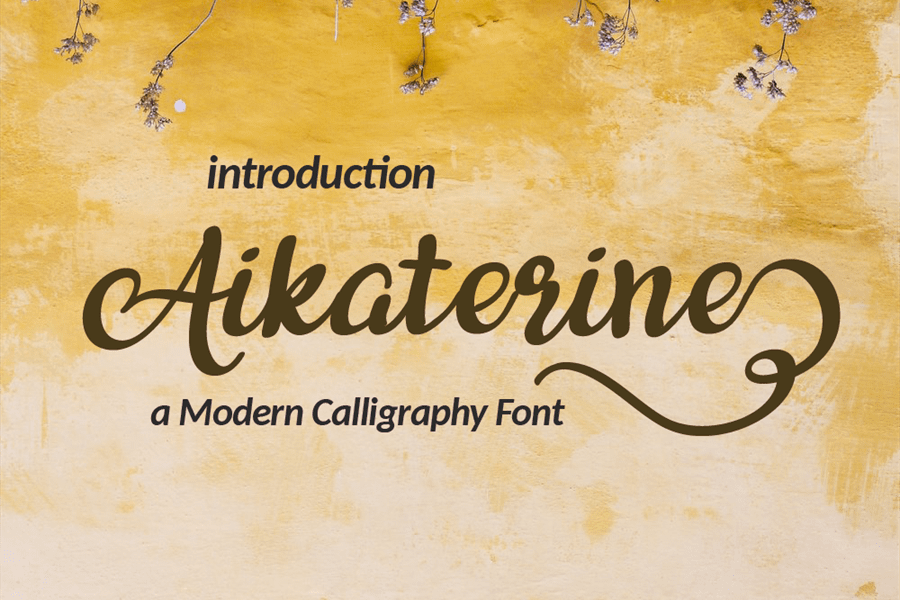
Aikaterine Font – Download Grátis
Aikaterine Font é uma elegante tipografia que oferece um fluxo natural e sofisticado. Perfeita para uma ampla variedade de projetos criativos, desde logotipos e identidades visuais até embalagens de produto e materiais promocionais como cartões de visita ou invitations. A fonte está equipada para criar designs únicos e encantadores para qualquer evento especial, tais como casamentos e eventos sociais, bem como para elementos específicos como marca d’água e posts nas redes sociais. Com seu estilo elegante e fluído, você pode adaptá-la a uma infinidade de estilos visuais e se destacar em uma vasta gama de mídias digitais. Descubra o encanto desta fonte de letras contínuas.